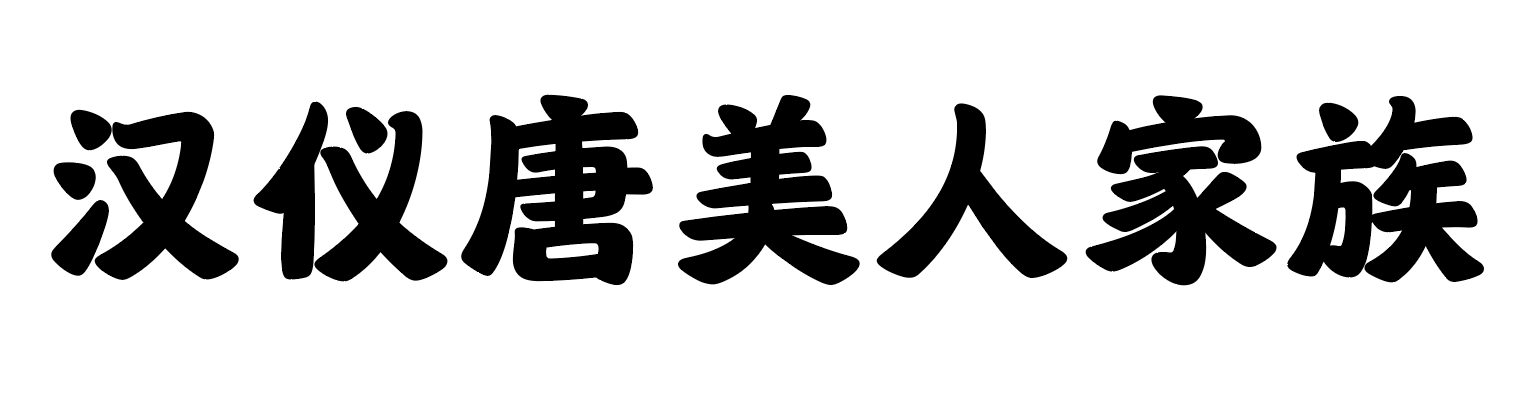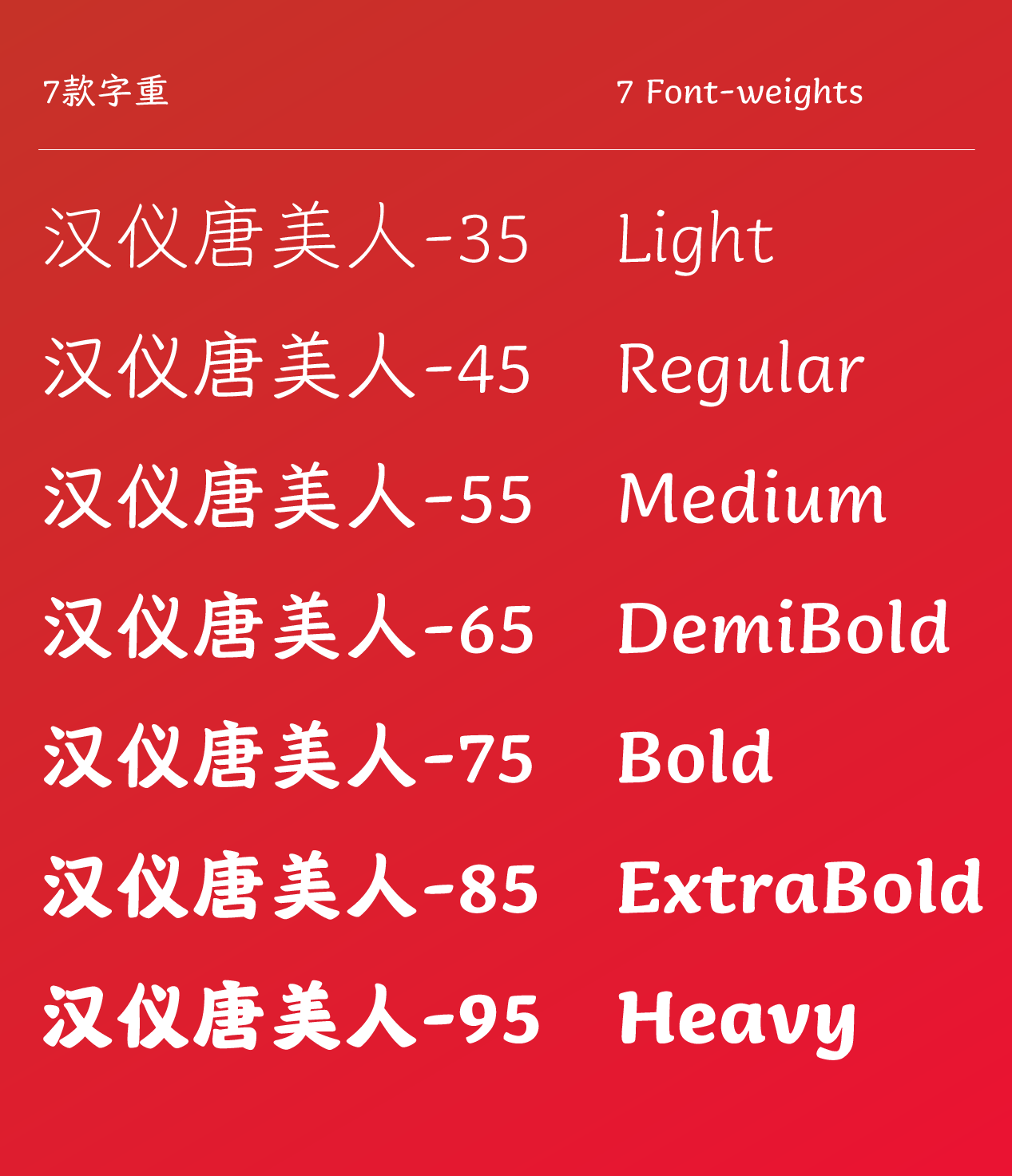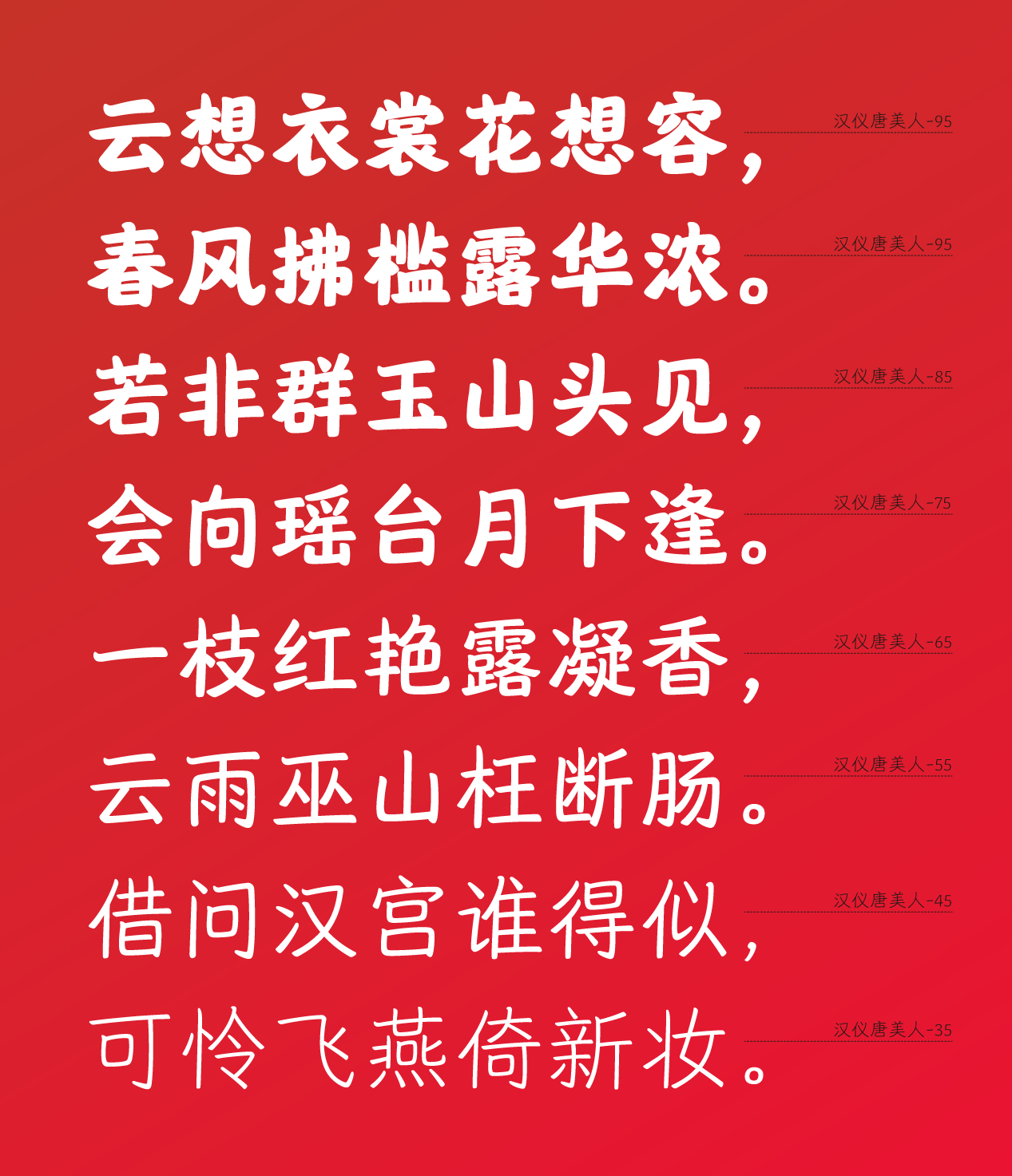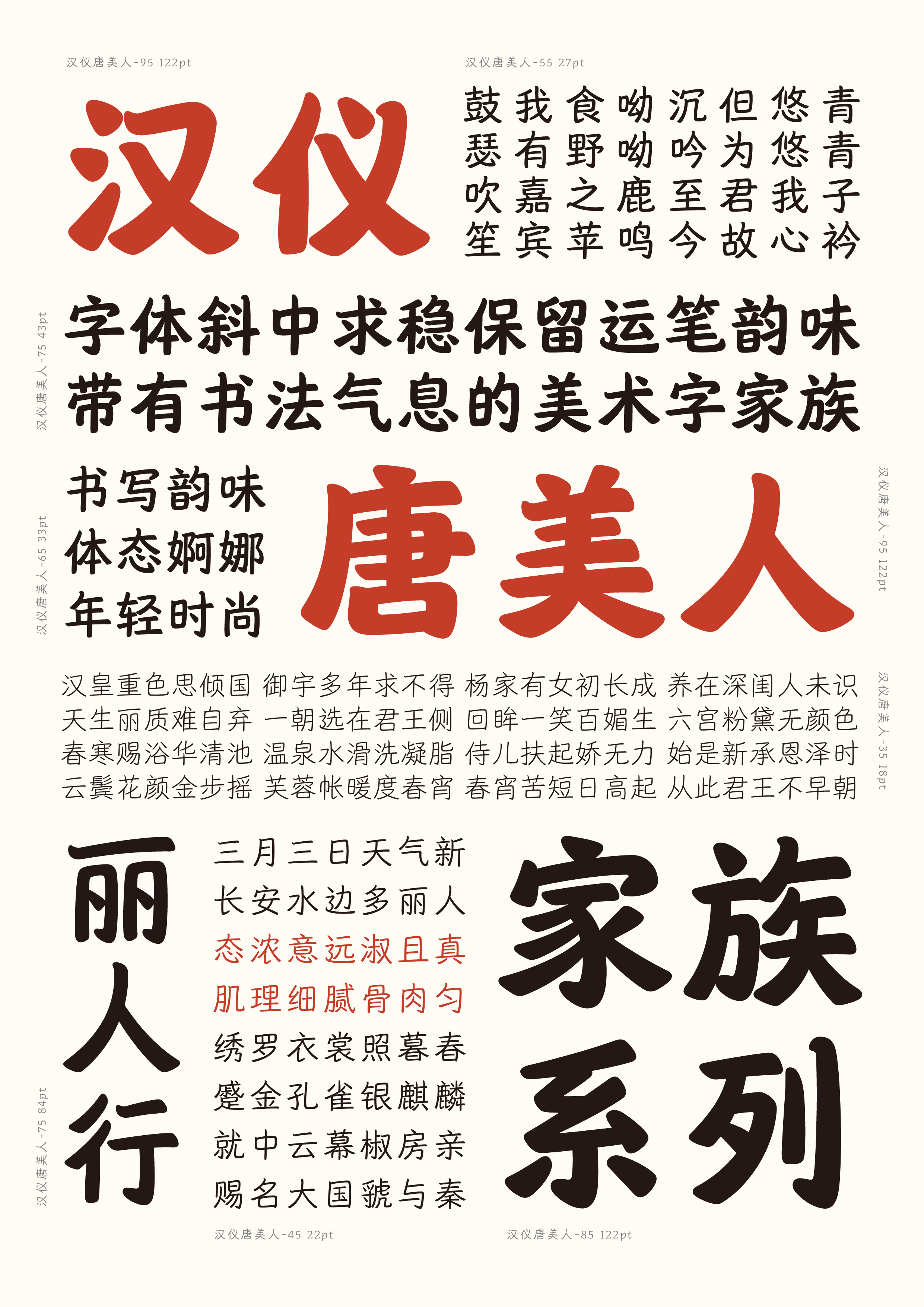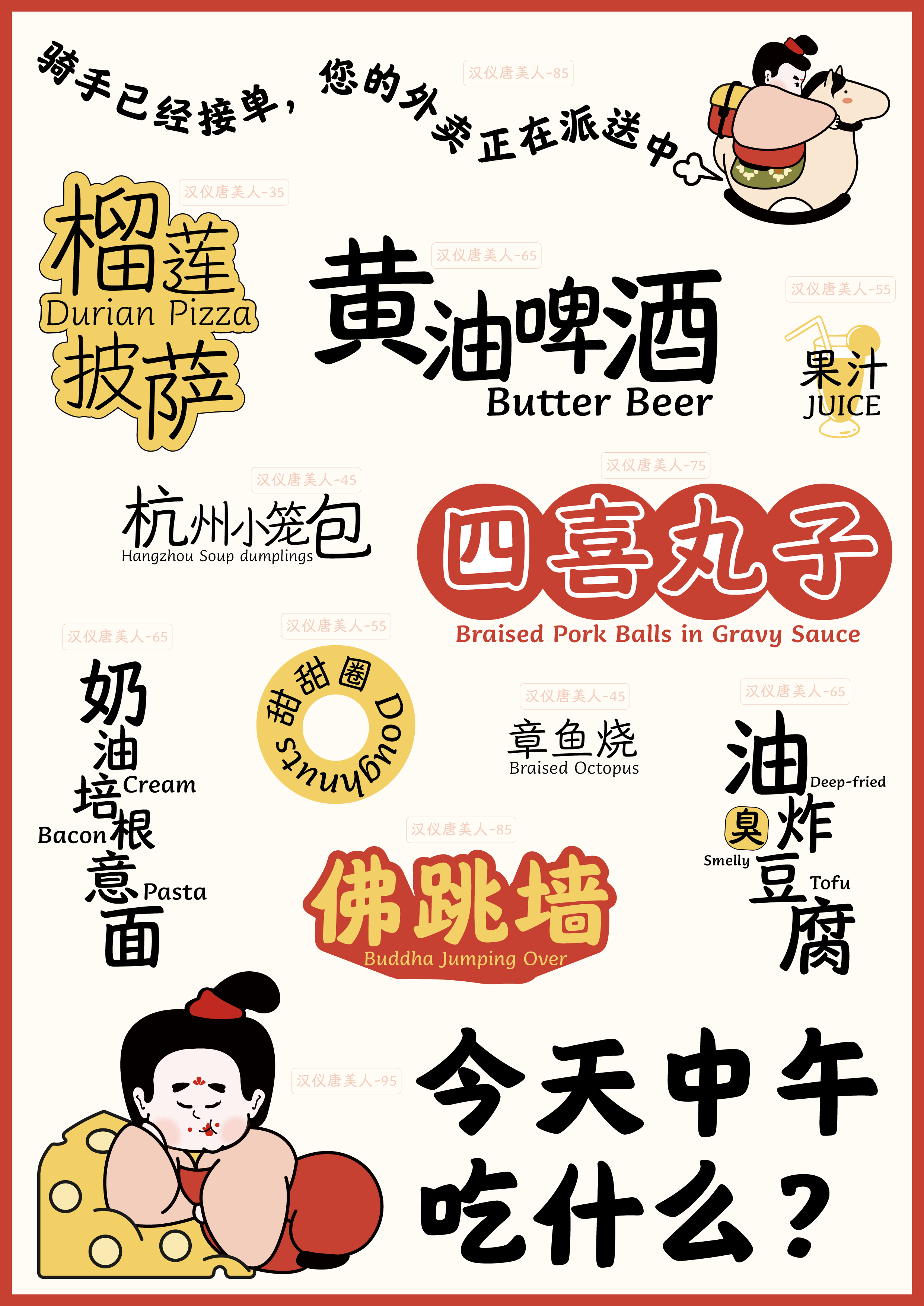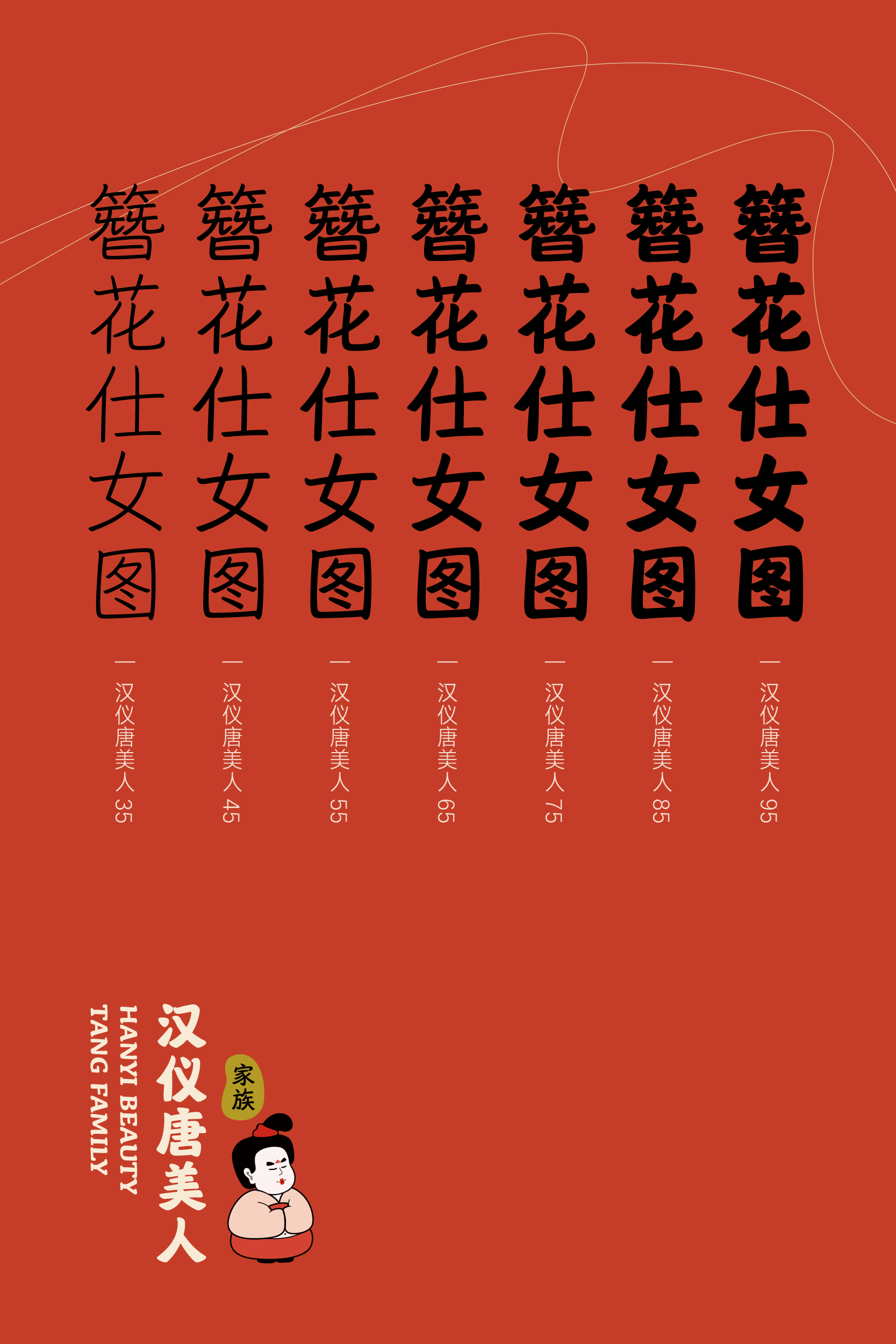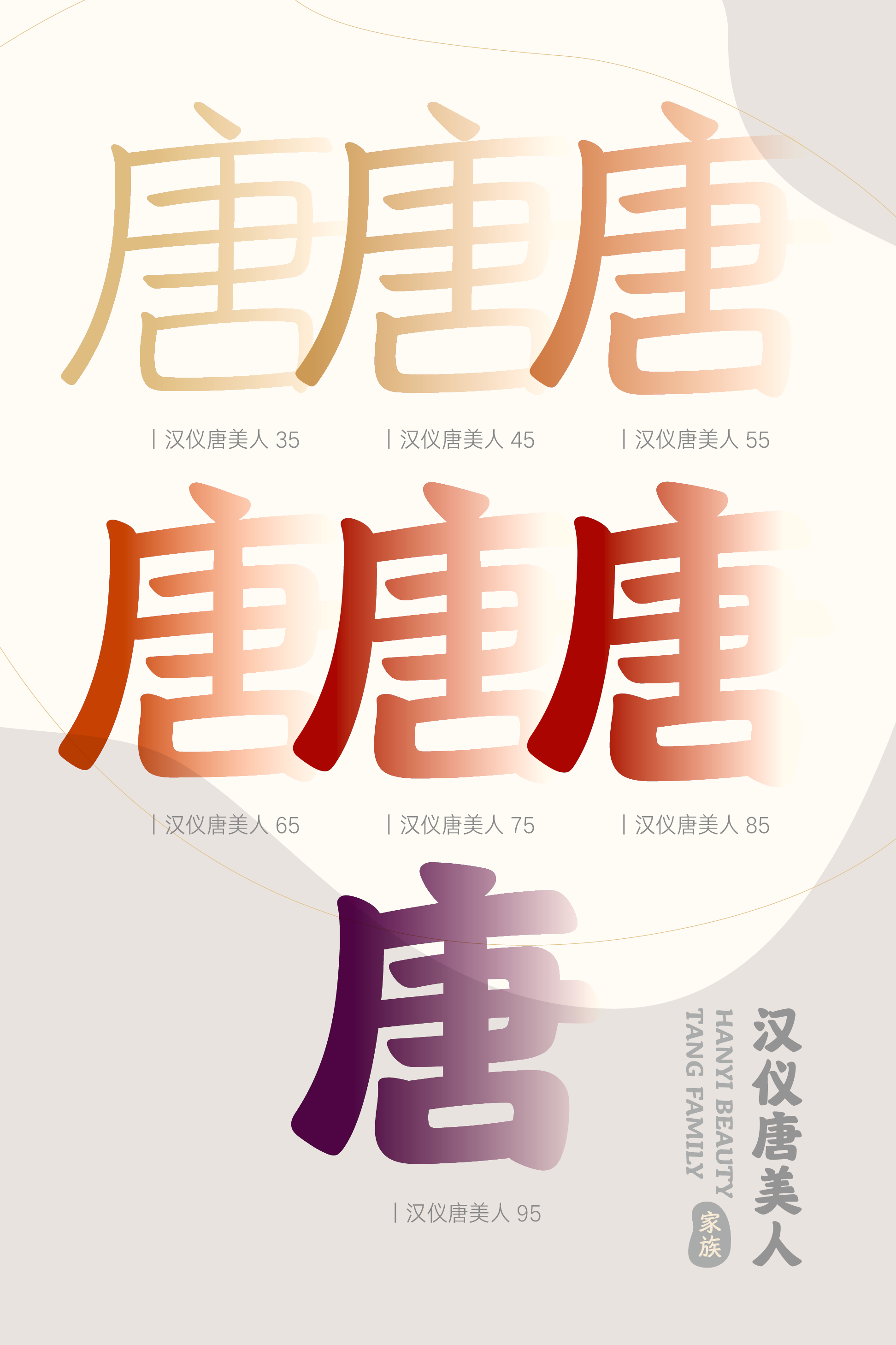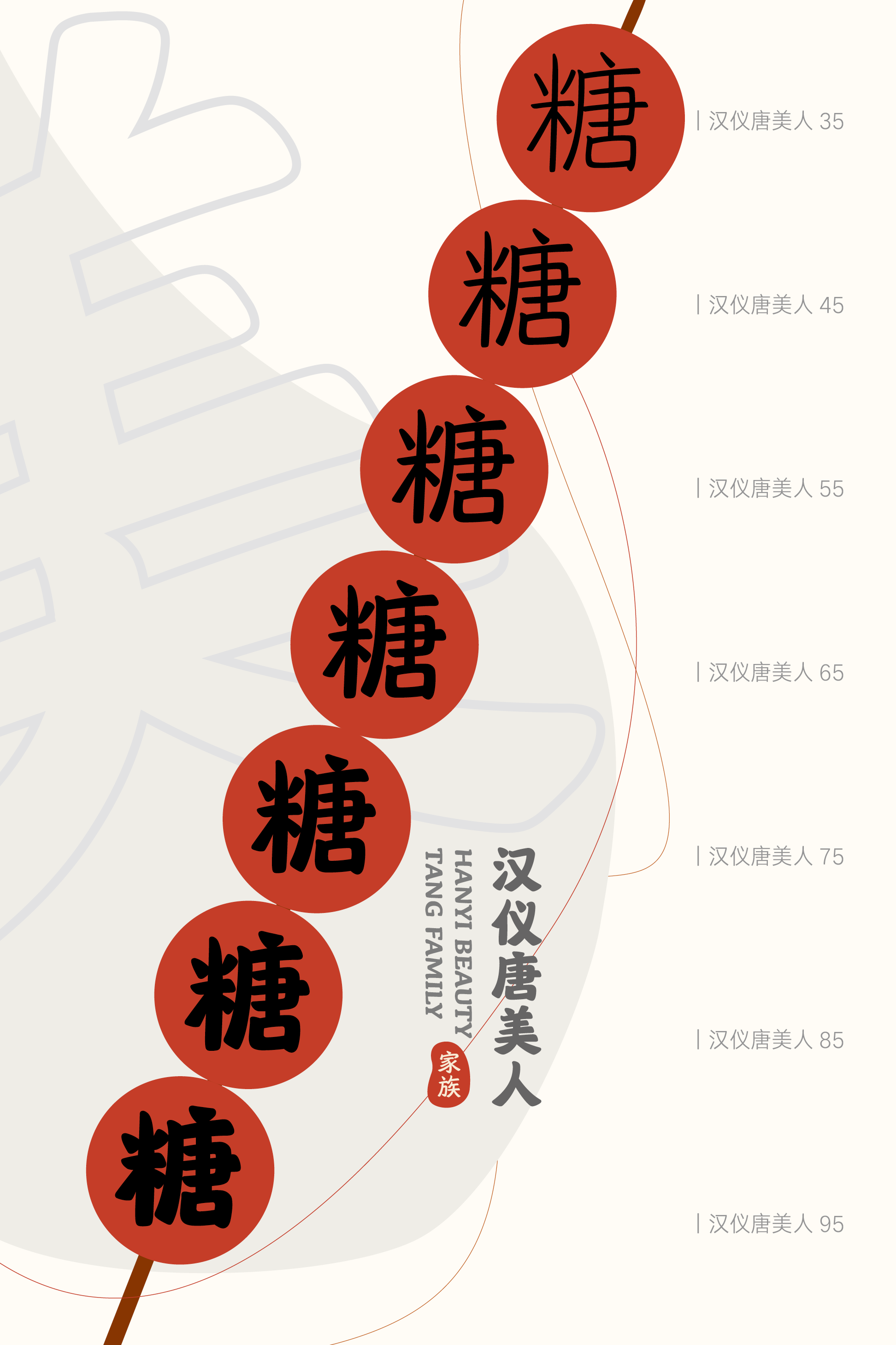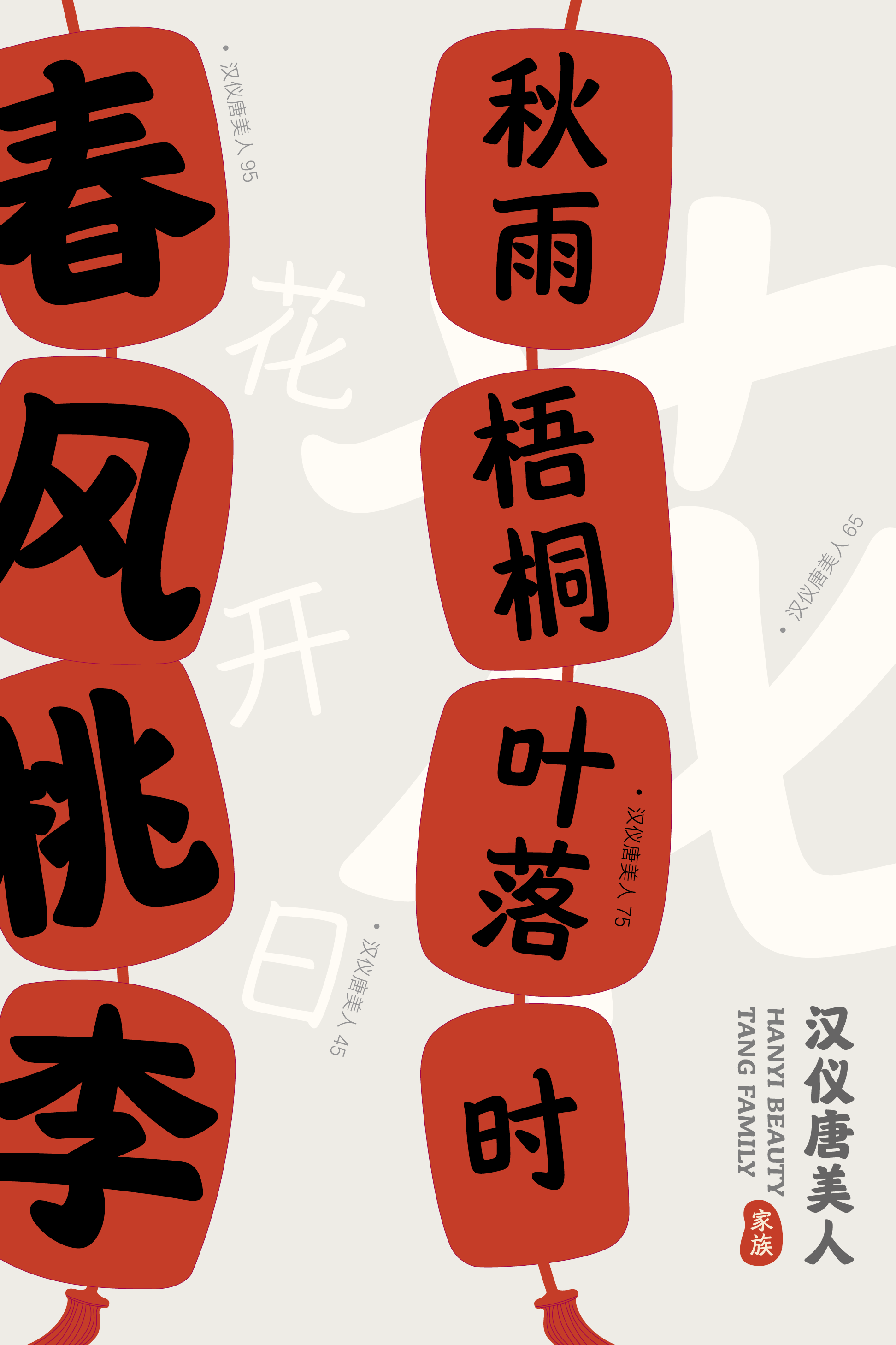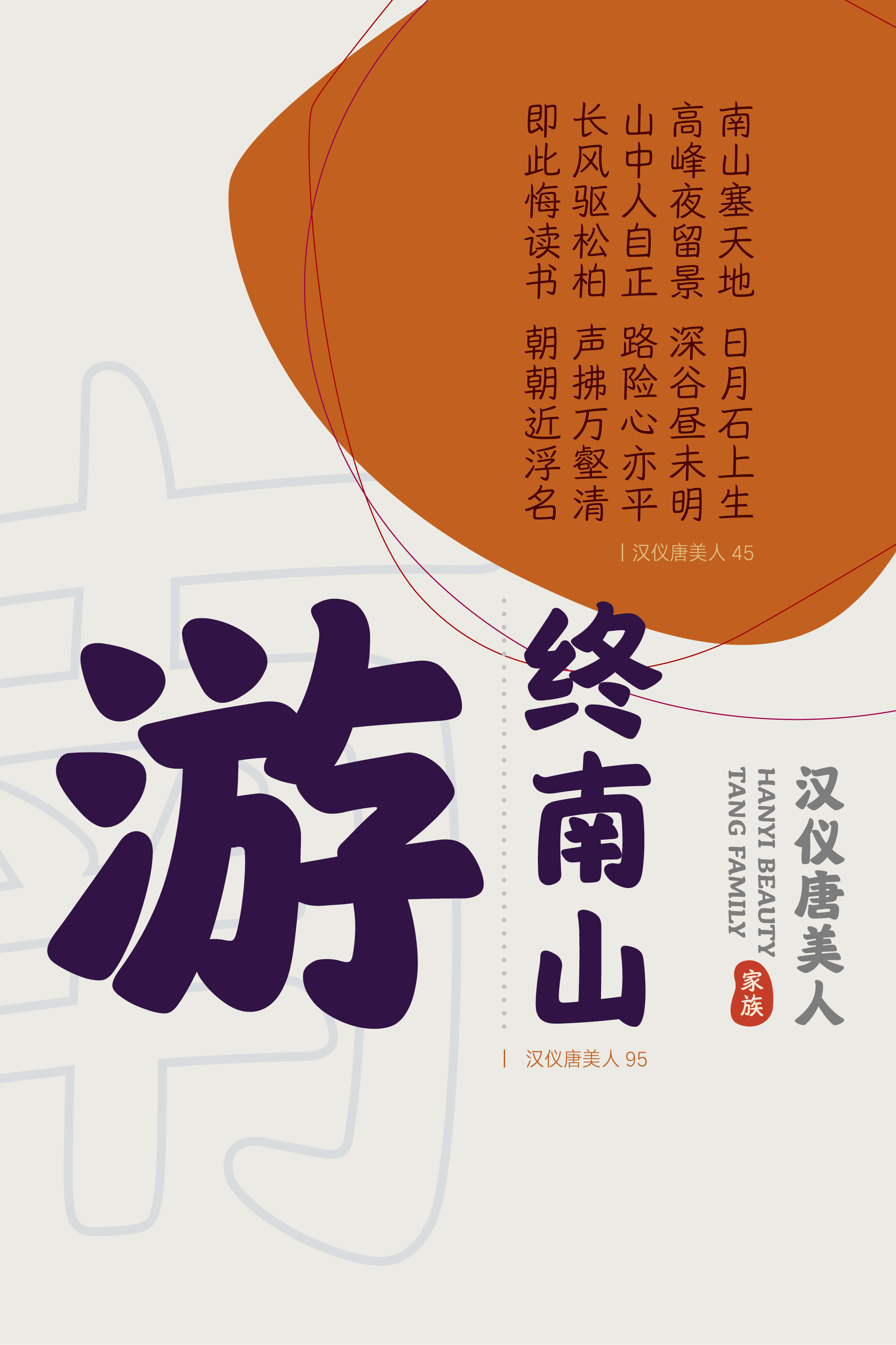
汉仪唐美人字体介绍,一款带有书写韵味的家族字体
汉仪唐美人家族|带有书写韵味的美术字
汉仪唐美人是一款带有书写韵味的家族字体,多款字重展现了唐代不同时期丽人的神韵之美,蕴含了初唐的清秀、娴雅,盛唐的丰丽和晚唐的舒展。
该字体家族共包含7个字重:汉仪唐美人35/45/55/65/75/85/95,满足了不同视觉层级的需求,为设计师的排版提供了更多方案。
汉仪唐美人家族|结构特点
汉仪唐美人家族的灵感源自赵之谦书法,结字方正,犹存隶书意韵。设计师在基于对传统书法的理解上加入了现代审美的时尚感,形成了体态婀娜,举止端庄大方的东方美人形象。
汉仪唐美人家族保留了书写时自然右上倾斜的态势,字体斜中求稳、重心一致、中宫放松、视觉张力强。作为一款美术风格家族字体,为现代字体注入了传统精神文化,展现了更多的东方美的姿态。
根据书写视觉效果,汉仪唐美人家族的左右部件成欹侧形,左低右高。相同偏旁保持着位置上的一致性,使整个字体在有个性的前提下不失逻辑。
汉仪唐美人家族的部件位置不同,处理方式也不尽相同,如“口”结构。
汉仪唐美人家族|笔画特点
汉仪唐美人家族捕捉书法痕迹,保留运笔韵味。横画略向右上方倾斜,起笔轻盈,中锋运笔,收笔有力,是一款凝聚书法气息的现代字体家族。
汉仪唐美人家族的横、竖、撇起笔均有顿笔动作。不仅合理的表现了字体的书写性,也增强了其装饰性。
汉仪唐美人家族|字重特点
汉仪唐美人家族有着“态浓意远淑且真,肌理细腻骨肉匀”的丽人姿态,细体如骨,婀娜多姿,粗体如肤,细腻丰腴。由最粗款过渡到最细款时,字体的气质和结构保持了一致性。
汉仪唐美人家族在不同字重的字体笔画衔接处理上注重细节,粗细调整使字体黑白空间更均衡,避免因笔画衔接不合理而导致的识别问题。
汉仪唐美人家族|功能特点
汉仪唐美人家族共7个字重,35/45/55/65/75/85/95。不是在视觉上将笔画均匀加粗和减细,而是逐渐趋向于正文排版的设计形式,让唐美人能够适应不同的排版需求。
汉仪唐美人家族|中西文匹配
汉仪唐美人家族的西文字母以意大利斜体风格为基础,用轻巧的衬线角与中文的书写感相呼应,设计出“肌肤丰润、胖瘦适中、身材匀称”的西文字母。
汉仪唐美人家族的西文字母细节处理别出心裁。通过夸张字母的造型和笔画的粗细对比,来丰富其细节变化。
汉仪唐美人家族|符号设计
汉仪唐美人家族的符号设计提取自唐代仕女的前额花钿,将妆容设计转化为图形符号的设计是设计师的别具匠心之处。
汉仪唐美人家族|样张展示
汉仪唐美人家族|字体海报